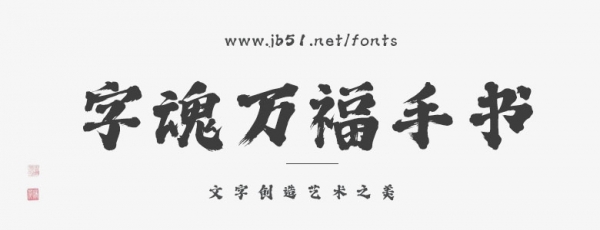
字魂萬福手書字體是由字魂創(chuàng)意字庫設計并生產(chǎn)的一款可商用的字體,被收錄于字魂先鋒系列。該字體支持GB-2312標準以及最新的字魂ZH7144標準,包含9507個中文、字母、符號和數(shù)字,字體類型偏向手寫體,具有豪放、中國風、帥氣的風格,在市面上廣泛用于活動促銷、印刷品&包裝、運動戶外等場景。